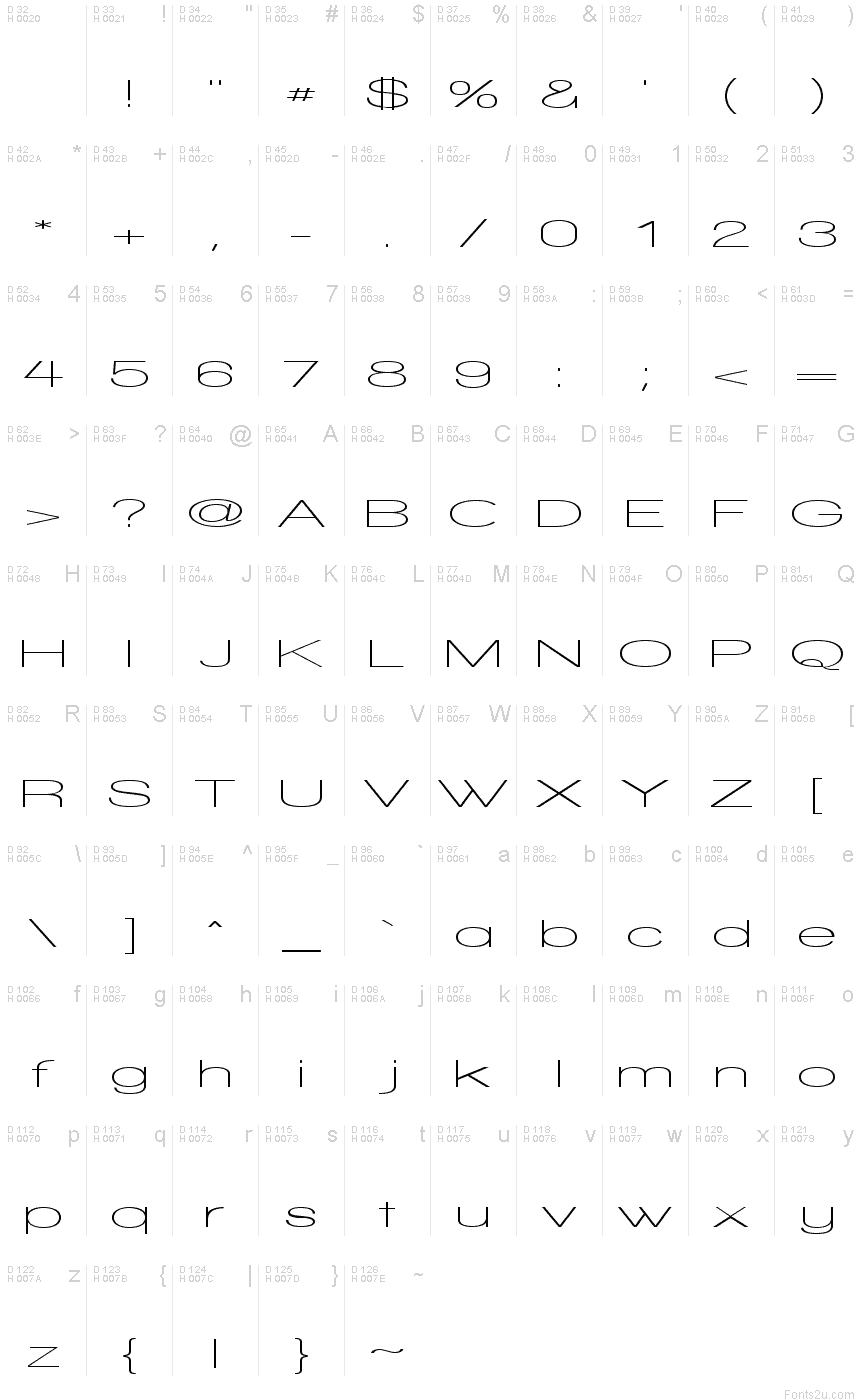
Walkway UltraExpand SemiBold
Walkway UltraExpand SemiBold di G.M. è un font geometrico sans serif gratuito dal ritmo architettonico ed essenziale. Le lettere sono caratterizzate da tratti molto sottili, spaziatura ampia e forme circolari e angolari semplici, che conferiscono al font un tono calmo e futuristico, richiamando più la segnaletica e il lettering modernista che i classici sans serif da lavoro.
Si adatta perfettamente al branding di progetti tech, poster di gallerie, sistemi di wayfinding, copertine di album e titoli in cui le parole brevi possono respirare. Essendo un font gratuito, è ideale anche per testate, copertine e iniziali in stile monogramma, poiché le forme allungate e ariose, insieme ai raccordi appuntiti, rendono anche una breve scritta incisiva e ben definita.